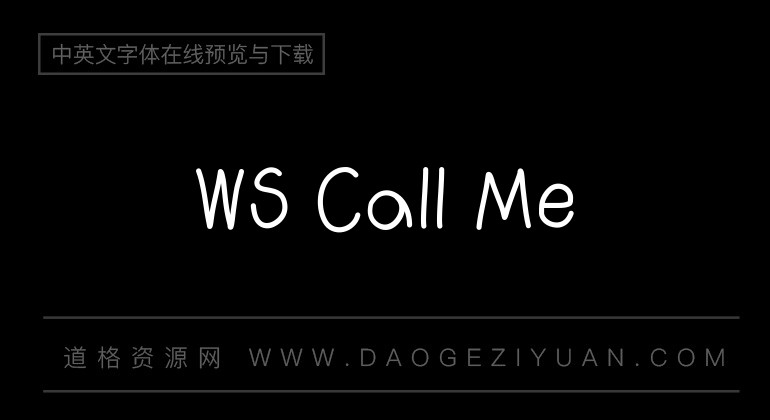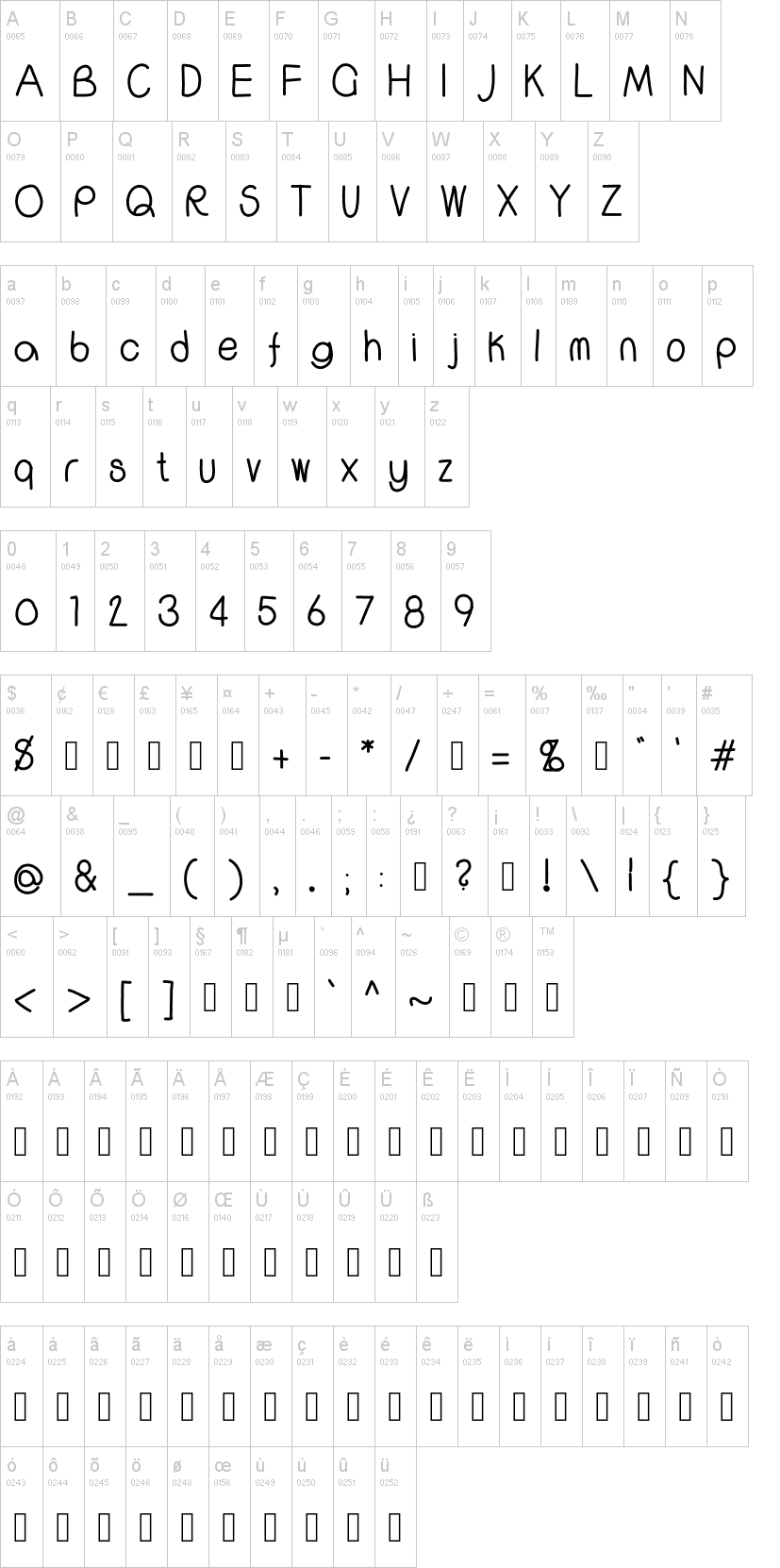
WS Call Me
? WS Call Me 字体是一款简洁、清新的英文字体,它的字母笔画细腻流畅,具有自然的美感,让文字更加清晰明了,显得更加清新优雅。它的字形设计更加符合当今流行的设计风格,可以满足各种不同的设计需求,是一款非常适合用于广告、海报、标志等设计的字体。
WS Call Me是一款非常不错的手写艺术字体,具有很好的视觉感,适合于文化类的宣传设计、商业类品牌的广告和产品包装设计以及个性化文字排版等较多场景。
WS Call Me字符映射图